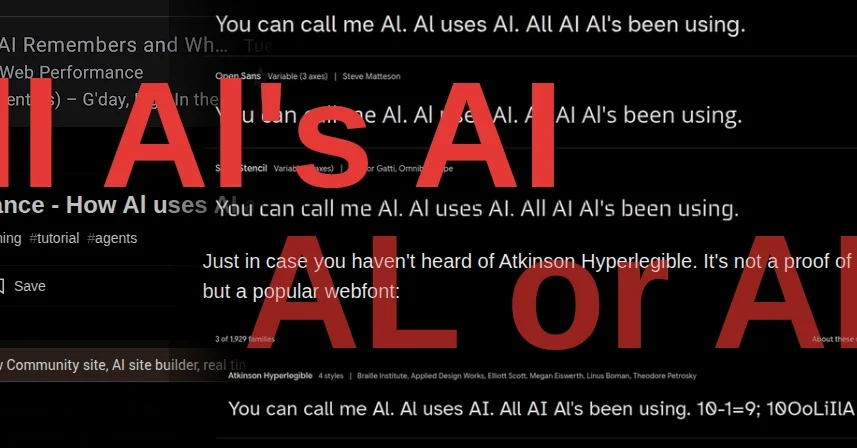
대문자 'I'와 소문자 'l'의 시각적 혼동으로 인해 웹 폰트(Web Font) 가독성 문제가 지속적으로 발생
접근성(Accessibility) 관련 법규 및 가이드라인에도 불구하고, 가독성이 낮은 웹 폰트 사용이 여전함
Atkinson Hyperlegible과 같은 가독성 높은 폰트가 존재하지만, Ubuntu와 같은 폰트도 가독성 개선에 기여
본문에서 지적하는 가장 큰 문제점은 웹 폰트(Web Font)에서 대문자 'I'와 소문자 'l'의 시각적 구분이 어렵다는 점이다.
특히, 좁은 화면이나 낮은 해상도 환경에서 가독성이 더욱 저하됨
이는 사용자 경험(UX) 저해는 물론, 정보 전달의 오류를 발생시킬 수 있음
Atkinson Hyperlegible과 같은 가독성을 고려한 폰트 사용이 대안으로 제시됨.
웹 접근성(Web Accessibility) 관련 법규 및 가이드라인에도 불구하고, 가독성이 낮은 폰트 사용이 여전한 현실을 지적한다.
WCAG(Web Content Accessibility Guidelines)와 같은 표준 준수가 의무화되었지만, 실질적인 개선은 미흡함
APCA(Advanced Perceptual Contrast Algorithm)와 같은 새로운 알고리즘 도입을 통해 가독성 개선을 기대
접근성 준수를 위해서는 폰트 선택뿐만 아니라, 폰트 크기, 자간, 행간 조절 등 다양한 요소들을 고려해야 함.
가독성 개선을 위해 Atkinson Hyperlegible과 같은 특정 폰트 사용을 권장하며, Ubuntu와 같은 폰트도 대안으로 제시한다.
Atkinson Hyperlegible: 시각적 구분이 쉽도록 디자인되어 가독성이 뛰어남
Ubuntu: 가독성과 미려함의 균형을 추구
폰트 선택 시, 디자인적 요소뿐만 아니라, 사용 환경(디바이스, 브라우저) 및 사용자 특성을 고려해야 함.